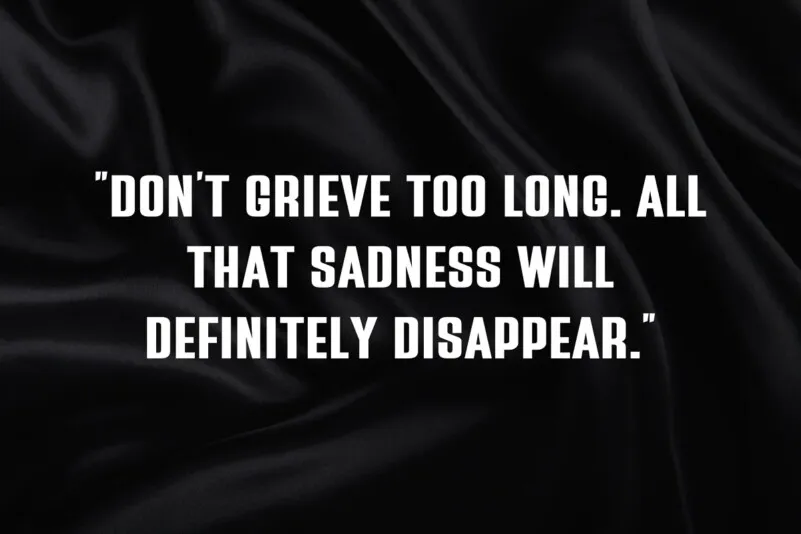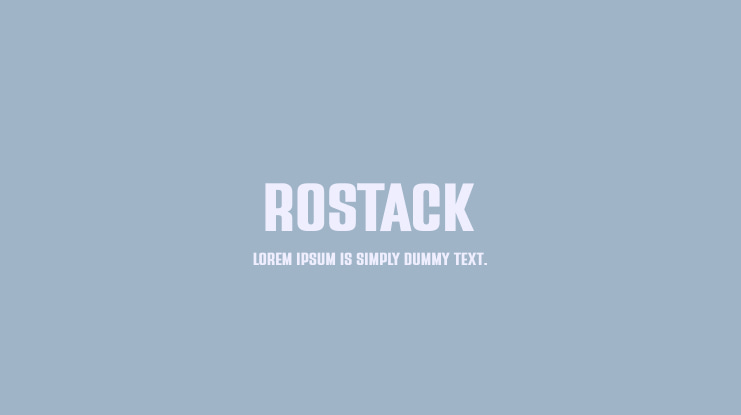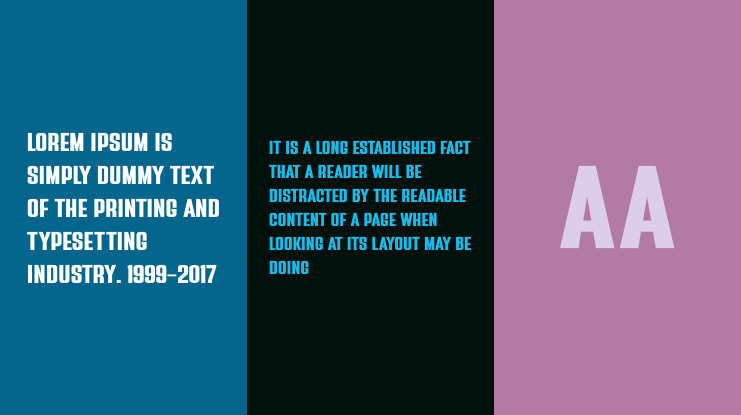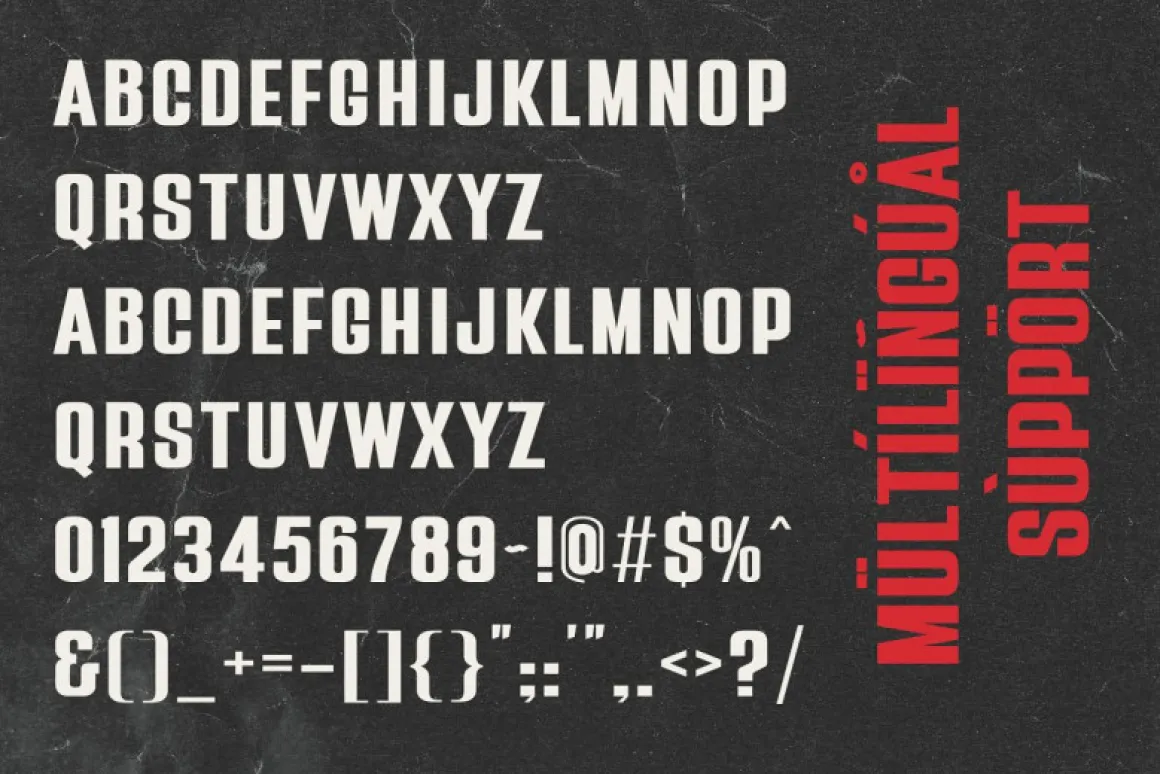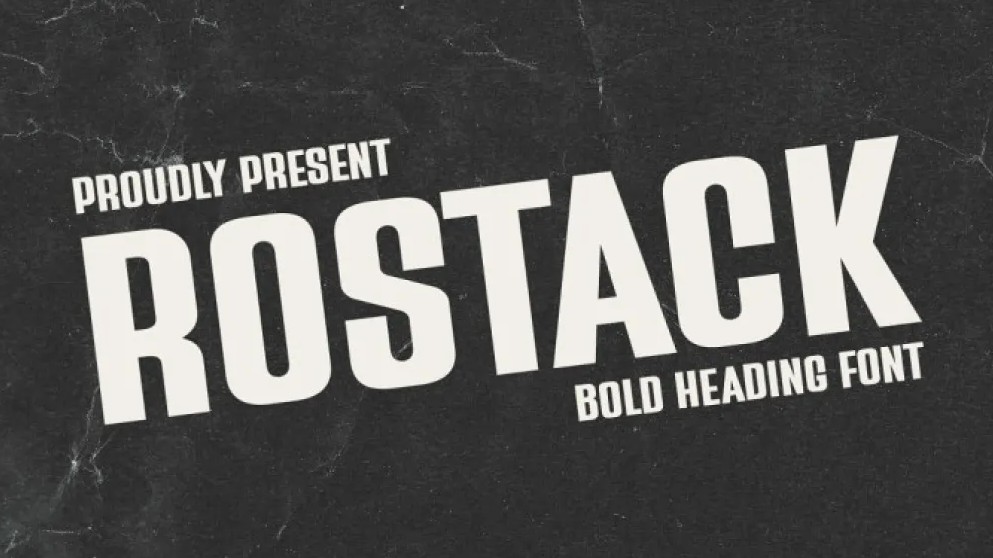
Font Rostack là bộ phông chữ thuộc dòng Display hình học mang phong cách công nghiệp mạnh mẽ, đậm chất đường phố và tràn đầy uy lực thị giác. Với cấu trúc nét chữ dày bản, các góc cạnh dứt khoát cùng tỷ lệ hình khối vững chãi, Rostack là lựa chọn số một cho các thiết kế logo thời trang Streetwear, bao bì thực phẩm bổ sung thể thao, hộp đựng phụ kiện gaming và ấn phẩm sự kiện sôi động. Doozypack.vn cung cấp link tải font Rostack Việt hóa chuẩn kỹ thuật, giúp bạn sở hữu phông chữ cá tính này mà không lo gặp bất kỳ lỗi hiển thị dấu thanh nào khi thiết kế in ấn.
Đặc điểm thẩm mỹ độc đáo của bộ font Rostack
Rostack không đi theo sự thanh mảnh của các phông chữ văn bản thông thường; nó được tạo ra để trở thành một khối nam châm thị giác thu hút trọn vẹn sự chú ý của người xem.
Phong cách Display hình học mạnh mẽ và dứt khoát
Đặc trưng lớn nhất của Font Rostack là các đường nét vuông vức, thẳng tắp với độ dày nét (weight) cực lớn. Cấu trúc chữ mô phỏng các khối bê tông kiên cố hay khung thép công nghiệp, tạo nên cảm giác vô cùng bền bỉ, uy tín và chắc chắn. Khi đặt Rostack làm tiêu đề trên bao bì, tên thương hiệu của bạn sẽ ngay lập tức khẳng định được vị thế vững vàng, bản lĩnh và phong thái dẫn đầu trên thị trường.
Sức hút thị giác vượt trội cho các tiêu đề lớn
Các ký tự của Rostack sở hữu tỷ lệ cô đọng theo chiều ngang kết hợp cùng chiều cao ấn tượng, tạo nên một mảng khối Typography đặc quánh và giàu năng lượng. Khoảng hở trong chữ (counter) được thu hẹp có chủ đích, giúp các dòng tiêu đề trên nắp hộp giấy hay mặt trước túi giấy hiển thị cực kỳ rõ ràng, dứt khoát và dễ dàng nhận diện từ khoảng cách xa trên các kệ hàng trưng bày.
03 Ưu điểm nổi bật của bản font Rostack Việt hóa
Khi ứng dụng các phông chữ nét dày vào thị trường trong nước, sự chỉn chu về dấu câu là yếu tố quyết định đến tính chuyên nghiệp của bản thiết kế:
- Khắc phục triệt để lỗi dấu tiếng Việt: Phiên bản Việt hóa đã được đội ngũ thiết kế trau chuốt thủ công từng dấu câu. Các dấu sắc, huyền, hỏi, ngã, nặng được vẽ vuông vức, dày dặn đồng điệu cùng thân chữ gốc, không gây cảm giác chắp vá hay đè nét làm mất tính thẩm mỹ công nghiệp.
- Bảo đảm tính đồng nhất thương hiệu: Việc tải font Việt hóa Rostack chuẩn giúp bạn tự tin dàn trang tiêu đề tiếng Việt mà không lo hiện tượng lỗi ô vuông hay nhảy về font hệ thống khô khan.
03 Ứng dụng thực tế của font Rostack trong sản xuất bao bì tại Doozypack.vn
Sự kiên cố và mạnh mẽ của Rostack mang lại hiệu ứng thị giác đắt giá trên các dòng sản phẩm bao bì thực tế do Doozypack.vn sản xuất:
- Hộp thực phẩm bổ sung thể hình (Whey Protein, Gym): Tiêu đề thương hiệu in bằng font Rostack kết hợp màu sắc tương phản mạnh tạo nên vẻ ngoài tràn đầy sức mạnh và kích thích tinh thần tập luyện.
- Bao bì phụ kiện Gaming & Thiết bị công nghệ: Nét chữ hình học góc cạnh tạo phong cách hầm hố, hiện đại cho các vỏ hộp tai nghe, bàn phím cơ hoặc chuột máy tính.
- Túi giấy thời trang Streetwear: Tên cửa hàng in khổ lớn bằng font Rostack màu đen trên túi giấy trắng cán màng mờ tạo phong cách tối giản, cá tính và cực kỳ sành điệu.
Lưu ý kỹ thuật khi in ấn với phông chữ nét dày Rostack
Việc sản xuất bao bì thực tế sử dụng các phông chữ có độ phủ mực lớn như Rostack đòi hỏi sự am hiểu kỹ thuật chuyên sâu tại xưởng in Doozypack.vn:
- Kiểm soát hiện tượng tràn mực (Dot Gain) tại khe chữ nhỏ: Các khoảng hở bên trong chữ cái (như chữ ‘e’, ‘a’, ‘o’) khá hẹp. Khi in trên giấy Kraft hút mực nhanh, mực có thể bị lan làm bít kín các lỗ hở này. Bạn nên giữ size chữ tiêu đề tối thiểu từ 10pt trở lên để bảo đảm độ sắc nét.
- Hệ màu CMYK chuẩn cho văn bản: Luôn chuyển thiết kế về hệ màu CMYK và đặt màu đen cho văn bản ở thông số K=100 để chữ sắc nét nhất, tránh hiện tượng nhòe màu do lé bản kẽm khi in chồng nhiều màu.